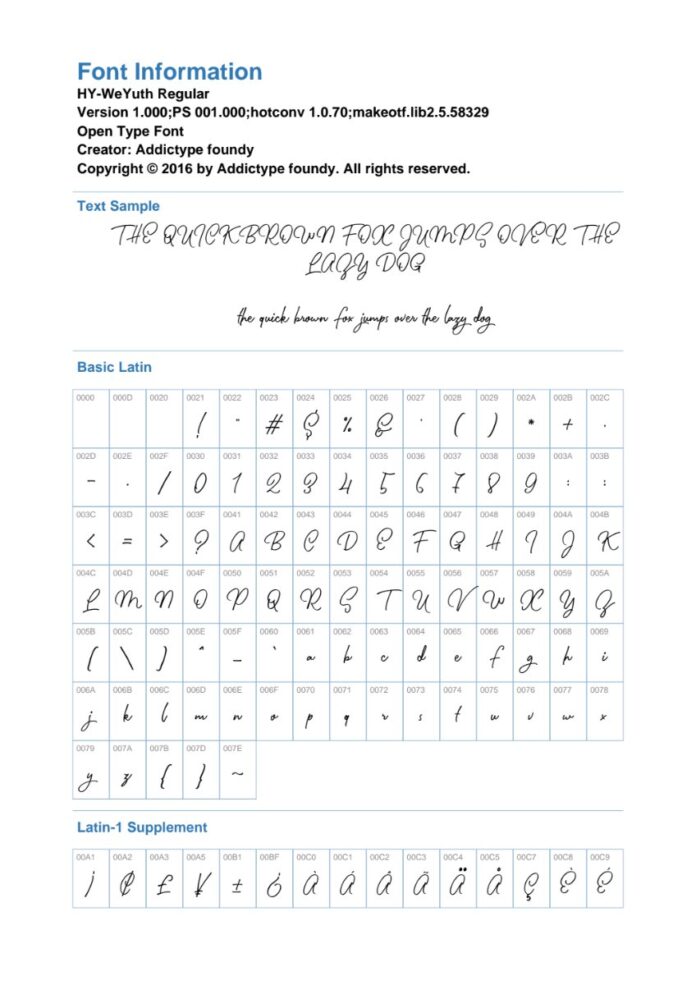
Font Chữ HY-WeYuth Đẹp, Miễn Phí
Giới thiệu về Font HY-WeYuth
Font HY-WeYuth là một kiểu chữ viết tay (script font) với phong cách hiện đại và thanh lịch. Được thiết kế bởi Addictype foundy, font chữ này nổi bật với các nét chữ mềm mại, liền mạch, tạo cảm giác tự nhiên như được viết bằng tay. Sự kết hợp giữa tính thẩm mỹ cao và khả năng đọc tốt đã giúp HY-WeYuth trở thành lựa chọn yêu thích của nhiều nhà thiết kế.
Đặc điểm nổi bật của Font HY-WeYuth
• Phong cách viết tay tự nhiên: Các ký tự được thiết kế với độ cong mềm mại, tạo cảm giác chân thực và cá nhân hóa.
• Tính linh hoạt cao: Phù hợp với nhiều loại hình thiết kế khác nhau, từ thiệp mời, logo, bao bì sản phẩm đến các ấn phẩm truyền thông.
• Dễ đọc: Mặc dù là font viết tay, HY-WeYuth vẫn đảm bảo tính dễ đọc, không gây khó khăn cho người xem.
• Hỗ trợ đa ngôn ngữ: Bao gồm các ký tự Latin cơ bản và Latin-1 Supplement, đáp ứng nhu cầu của người dùng quốc tế.
Ứng dụng của Font HY-WeYuth trong thiết kế
Với vẻ đẹp độc đáo của mình, font HY-WeYuth có thể được ứng dụng rộng rãi trong nhiều lĩnh vực thiết kế:
Thiết kế Logo và Nhận diện thương hiệu
Font HY-WeYuth mang đến sự sang trọng và cá tính cho các thiết kế logo. Đặc biệt phù hợp với các thương hiệu muốn thể hiện sự tinh tế, thủ công hoặc mang tính cá nhân hóa cao như cửa hàng thời trang, tiệm bánh, studio ảnh cưới, hoặc các dịch vụ làm đẹp. Việc sử dụng font này giúp tạo ra một ấn tượng mạnh mẽ và độc đáo cho thương hiệu của bạn.
Thiệp mời và Thiệp chúc mừng
Với các nét chữ uyển chuyển, HY-WeYuth là lựa chọn lý tưởng cho thiệp cưới, thiệp sinh nhật, thiệp mời sự kiện hoặc các loại thiệp chúc mừng khác. Font chữ này sẽ làm tăng thêm vẻ lãng mạn, ấm áp và trang trọng cho thông điệp của bạn, khiến người nhận cảm thấy đặc biệt và được trân trọng.
Bao bì sản phẩm và Nhãn mác
Trong thiết kế bao bì, font HY-WeYuth có thể giúp sản phẩm của bạn nổi bật trên kệ hàng. Nó tạo cảm giác về chất lượng thủ công, sự tinh tế và độc đáo, đặc biệt phù hợp với các sản phẩm cao cấp, sản phẩm hữu cơ hoặc các mặt hàng thủ công mỹ nghệ. Một nhãn mác được thiết kế với HY-WeYuth sẽ thu hút ánh nhìn và truyền tải thông điệp về sự chăm chút đến từng chi tiết.
Ấn phẩm truyền thông và Quảng cáo
Từ poster, banner đến các bài đăng trên mạng xã hội, font HY-WeYuth có thể làm cho tiêu đề hoặc các đoạn văn ngắn trở nên thu hút hơn. Nó giúp tạo điểm nhấn thị giác, truyền tải thông điệp một cách mềm mại nhưng vẫn đầy sức hút. Các chiến dịch quảng cáo sử dụng font này thường mang lại cảm giác gần gũi, thân thiện và đáng tin cậy.
Thiết kế website và UI/UX
Trong thiết kế website, font HY-WeYuth có thể được sử dụng cho các tiêu đề, slogan hoặc các yếu tố trang trí để tạo điểm nhấn. Nó giúp website trở nên độc đáo và có phong cách riêng, đặc biệt phù hợp với các trang web về nghệ thuật, thời trang, blog cá nhân hoặc các cửa hàng trực tuyến muốn tạo cảm giác sang trọng và tinh tế.
4. Kết hợp: Để tạo ra một thiết kế hài hòa, hãy thử kết hợp HY-WeYuth với các font chữ sans-serif hoặc serif đơn giản. Điều này giúp tạo sự cân bằng và làm nổi bật vẻ đẹp của font viết tay.
Font HY-WeYuth phù hợp với những loại thiết kế nào?
Font này rất phù hợp cho thiết kế logo, thiệp mời, bao bì sản phẩm, ấn phẩm quảng cáo, và các dự án cần sự tinh tế, cá nhân hóa.